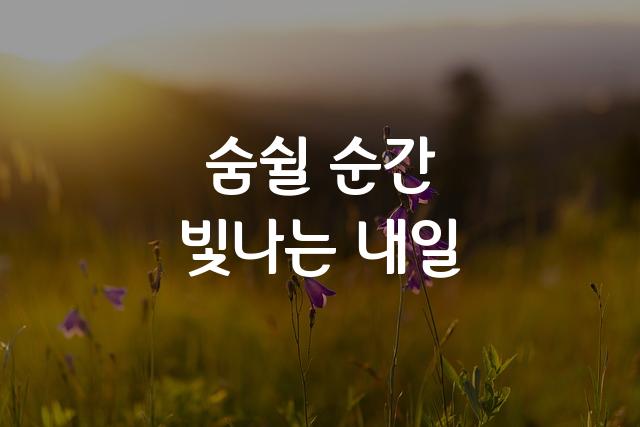
잘풀리는하루체는 기본 고딕 스타일을 바탕으로 문서 작성에 최적화된 폰트입니다. 부드러운 곡선과 세련된 디테일이 특징이며, 간결하고 명확한 표현력을 자랑합니다.
잘풀리는하루체은(는)
기본 고딕, 감성적인, 부드러움 계열의 생김새를 가지고 있으며
어린이 책, 인사말 카드, 일기/편지 등에서 자주 활용되며, 효과적인 메시지 전달에 적합합니다.
이 폰트는 음식/식음료, 라이프스타일, 유아/가족 분야에 잘 어울리며,
친근한, 귀여운, 편안한 느낌을 담고 있는 것이 특징입니다.
이 폰트와 유사한 폰트로는 Noto Sans KR, 맑은 고딕, Apple SD Gothic Neo 등이 있어요. 함께 비교해 보시면 좋습니다!